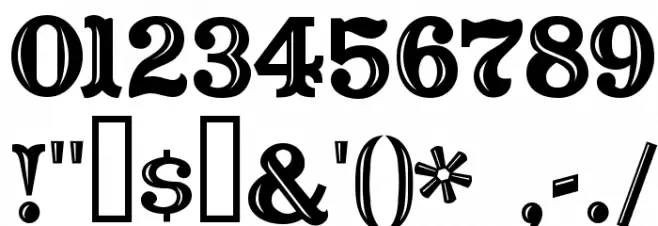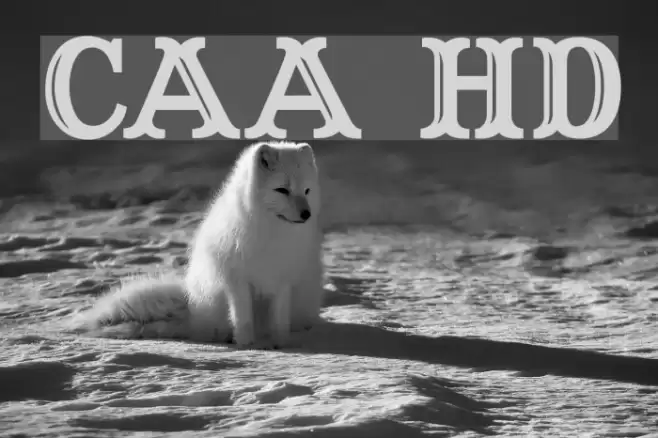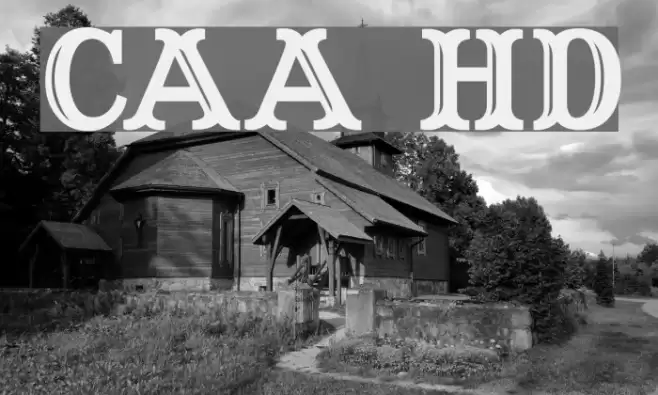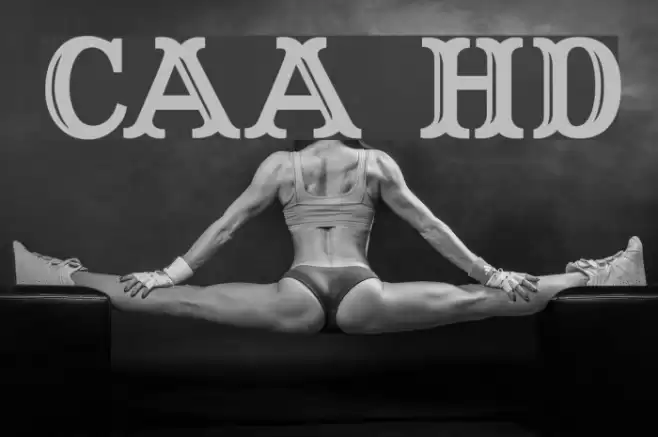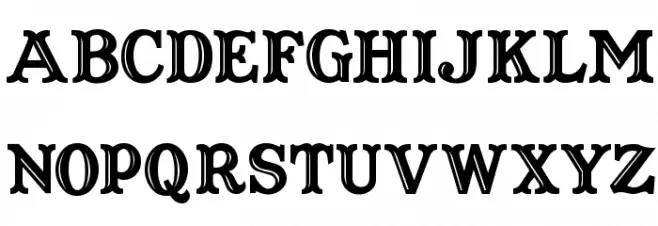
Captain Howdy Font
✎ Western
| समग्र शैली | Vintage |
| उपयोग का मामला | Headlines, Logos, Posters |
| सुझाए गए प्रोजेक्ट | Ideal for vintage-themed posters, eye-catching headlines, branding, and logo design. |